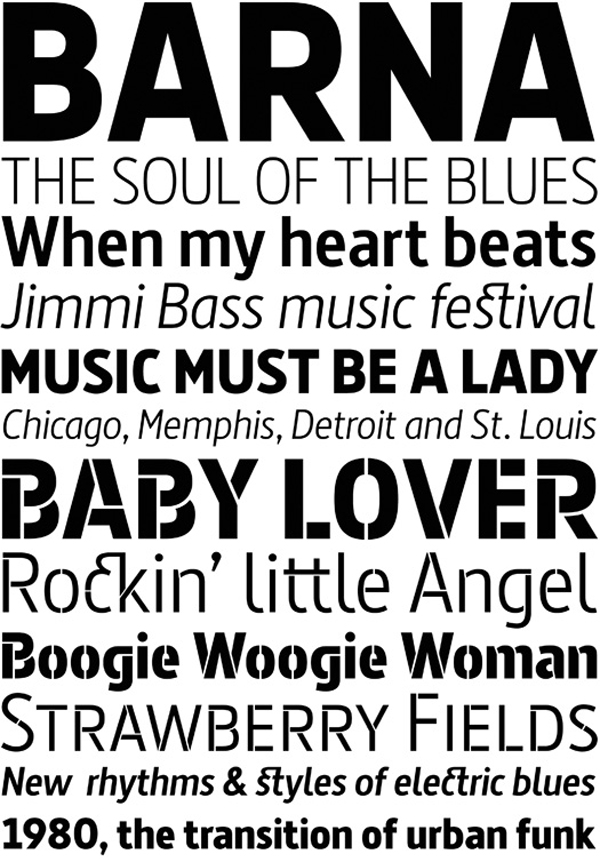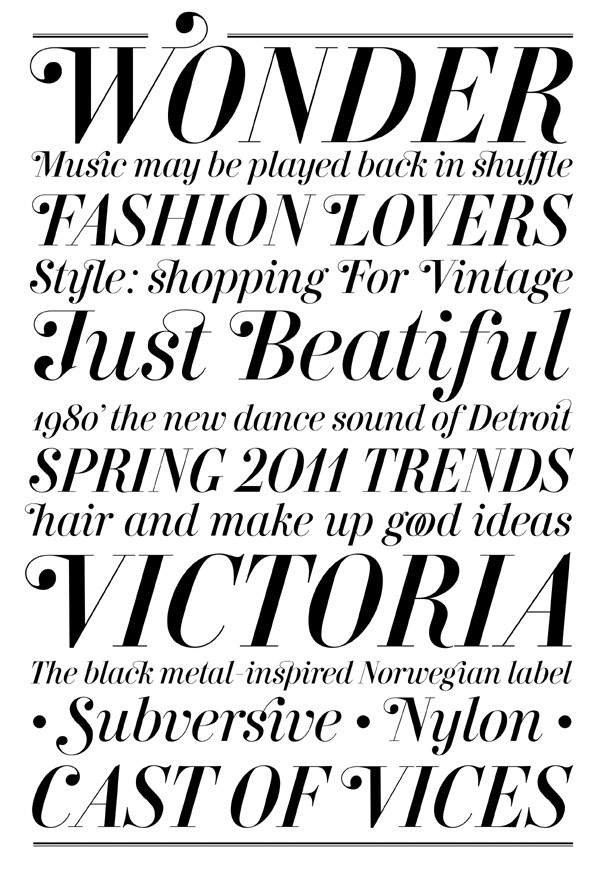
Una nueva versión de Carmen, Barna y Al-Andalus, la primera tipografía multilingüe diseñada en España, son los nuevas creaciones de Andreu Balius, tipógrafo y diseñador de tipografía de prestigio internacional que no para de trabajar.
La firma Victoria's Secret lleva casi un año utilizando la tipografía Carmen, creada por el propio Andreu Balius, en catálogos de ropa, lencería, etc., tanto en soporte papel como en la web. En otoño de 2010 el departamento de comunicación le pidió el diseño de un tipo cursivo, una Carmen Display Italic que completara la familia. Se trata de una fuente con un set muy extenso de caracteres: todos los necesarios para cualquier lengua que utilice el alfabeto latino, más ligaduras, caracteres ornamentales, numerales (alineados, elzevirianos, versalitas, índices, subíndices y tabulados), signos de puntuación, etc.
"La clave al diseñar una tipografía para una marca es que las formas acaben destilando los valores de dicha marca. En este caso, además, he querido darle a la nueva Carmen un aspecto más sensual, elegante y sofisticado”. Consciente de la importancia de la tipografía en el diseño gráfico corporativo señala: “Es decisiva. Pero en España todavía no se ha visto el enorme potencial que tiene la tipografía como manera de expresar los valores de una marca o producto”.
Tipo Carmen Display Italic para Victoria's Secret, Andreu Balius, 2011.
En su línea de trabajo personal para Typerepublic.com, ha publicado recientemente Barna. Tras un encargo de tipografía para señalización de la empresa Signes, Barna es una evolución de esta, una extensa familia para la composición de textos, que aporta los valores de simplicidad y de economía básicos para lectura rápida. Dispone de una buena proporción en altura y un ancho ligeramente reducido que permite un mayor número de caracteres por línea. A la familia Barna le acompaña una variante estarcida (Barna stencil), en proceso de ampliación. “Actualmente, estoy trabajando en la ampliación hacia variantes más estrechas (Barna condensed light, regular, bold, black) que estarán listas este próximo verano. Barna, con sus formas redondeadas y amables pretende ser una respuesta local a la multitud de tipos grotescos y de palo seco de clara ascendencia centroeuropea; un tipo moderno pero con sabores mediterráneos (contemporáneo en sus formas, funcional y económico pero, también, cálido y amable)”.
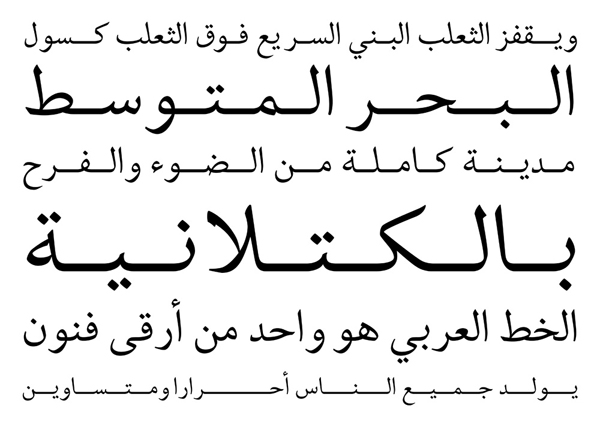
Tipo Al-Andalus, Andreu Balius, 2011.
Otro proyecto recién terminado es Al-Andalus, una nueva tipografía árabe. "Han sido tres años invertidos en un proyecto personal y con una clara vocación social, ligado al compromiso del diseño con la mejora del mundo en el que vivimos, en la responsabilidad social del diseñador gráfico". Pensada como una ayuda al diálogo intercultural mediante la visibilidad de lenguas diferentes ya que existen muy pocas fuentes tipográficas que contengan ambos sistemas de escritura —alfabeto Latino y alfabeto Árabe— con la finalidad de que ambos puedan convivir en la misma página y funcionen bien, a nivel de mancha tipográfica.
"Es difícil combinar tipografías árabes con tipografías latinas, pues son sistemas de escritura muy diferentes entre sí. En nuestra sociedad actual será cada vez más necesaria la disponibilidad de tipografías que permitan la composición de textos multilingües, que combinen sistemas de escritura diferentes. Para crearla el diseñador realizó un trabajo inicial de investigación sobre la tipografía árabe en España, de la que encontró algunas muestras del siglo XVIII que le han servido para establecer conexiones históricas con los tipos de Eudald Pradell".
Cartel del Congreso AGI OPEN Barcelona 2011, detalle logo Kyle Cooper, 2011. Imagen gráfica de Mario Eskenazi.
El diseñador, profesor y escritor forma parte de la organización del Congreso AGI OPEN Barcelona 2011, que reunirá en Barcelona el próximo mes de octubre, bajo el lema “What. How. Why”, a lo mejor de la tipografía internacional: Marian Bantjes, Michael Bierut, Nicholas Blechman, Irma Boom, Tony Brook, Kyle Cooper, William Drenttel, Mário Feliciano, Isidro Ferrer, James Goggin, Joost Grootens, Jessica Helfand, Steven Heller, Angus Hyland, Chip Kidd,Henrik Kubel, Anette Lenz, Javier Mariscal, Lars Müller, Christoph Niemann, Stefan Sagmeister, Paul Sahre, Ahn Sang-Soo, Paula Scher, Pierre di Sciullo, Marina Willer y Jan Wilker.